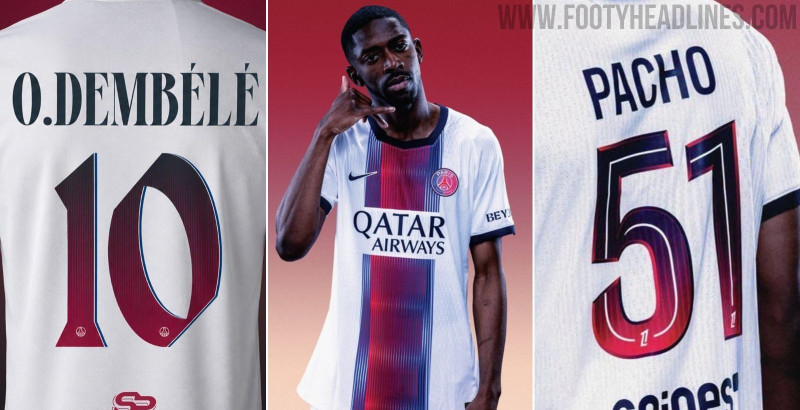
Se han publicado las tipografías de la camiseta visitante del PSG 26-27
• Confirmación de Tipografías: Se ha confirmado la tipografía oficial para la camiseta visitante del París Saint-Germain de la temporada 2026-27, aunque el PSG no ha mostrado los diseños completos.
• Dos Variantes de Diseño: La camiseta visitante del PSG para la temporada 26-27 empleará dos variantes de tipografía: una específica para la Liga de Campeones y otra para la Ligue 1.
• Detalles del Estilo: La tipografía de la Liga de Campeones se inspira en el Art Déco, mientras que la de la Ligue 1 es simplificada y presenta un degradado.
Ya se ha confirmado la tipografía oficial de la camiseta visitante del París Saint-Germain para la temporada 2026-27, tras su presentación oficial y según la información de La Source Parisienne, una fuente cercana al PSG. Por desgracia, el PSG no nos deja ver las tipografías al completo.
Tipografía de la camiseta visitante del PSG 26-27
Liga de Campeones y Ligue 1.
En la próxima camiseta de visitante se usarán dos variantes de la tipografía. La versión de la Liga de Campeones presenta los nombres y los números de los jugadores estilizados, inspirados en el Art Déco, mientras que el diseño tipográfico de la Ligue 1 se basa en el tipo de letra simplificado, pero también incluye un degradado.
Liga de Campeones: camiseta visitante del PSG para la temporada 26-27 de la Liga de Campeones
Camiseta visitante del PSG para la Ligue 1 26-27